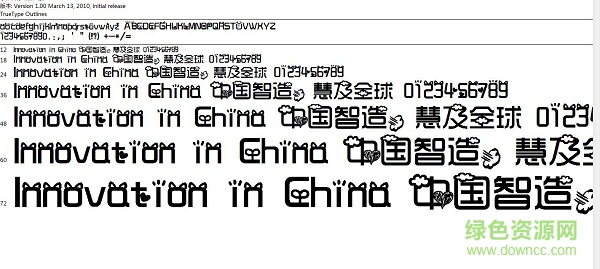
七叔ragingfire常規(guī)字體是一款獨(dú)特的廣告字體,字面裝飾多,字形帶有云朵、愛(ài)心、貓咪耳朵、氣團(tuán)、嫩芽等裝飾,給人的印象非常深刻,喜歡的朋友快來(lái)下載吧!
有鮮明的節(jié)奏韻律感,色彩豐富明快,給人以生機(jī)盎然的感受。這種個(gè)性的字體適用于兒童用品、運(yùn)動(dòng)休閑、時(shí)尚產(chǎn)品等主題。